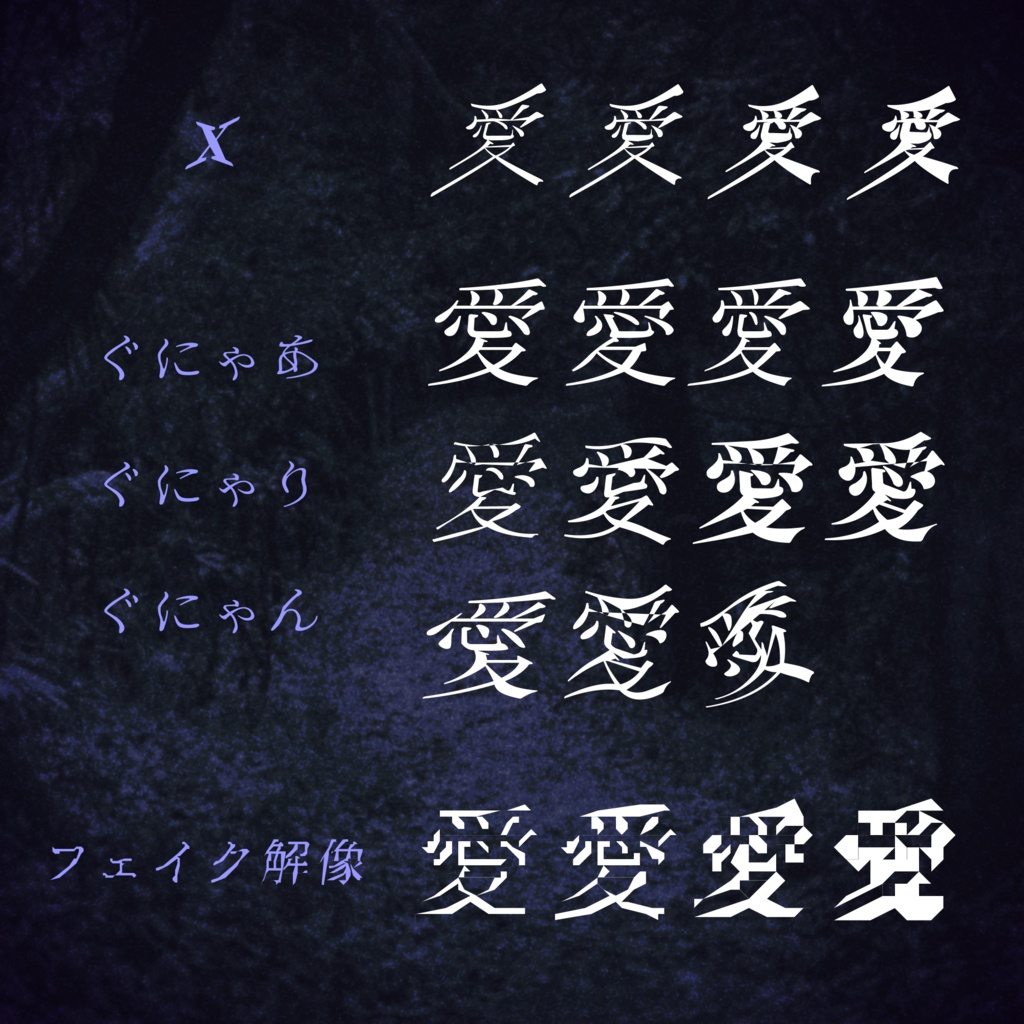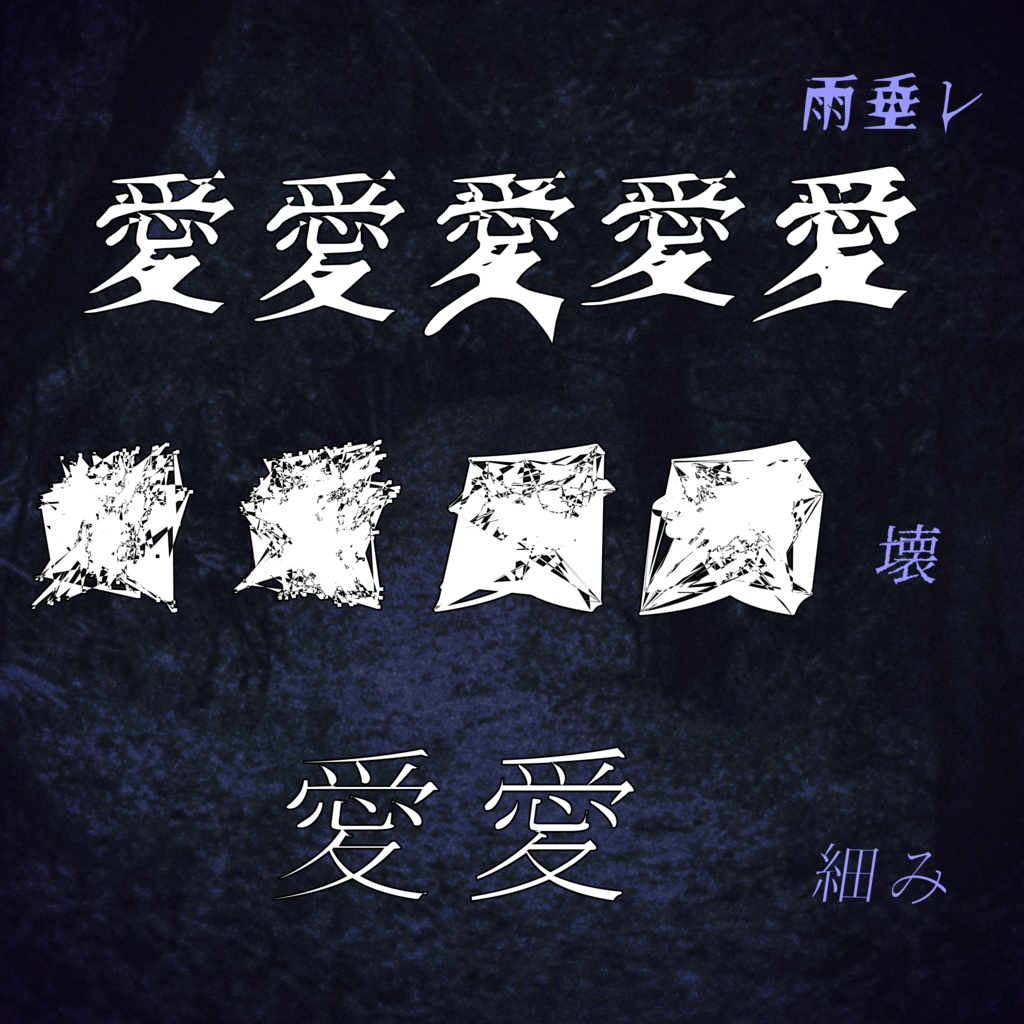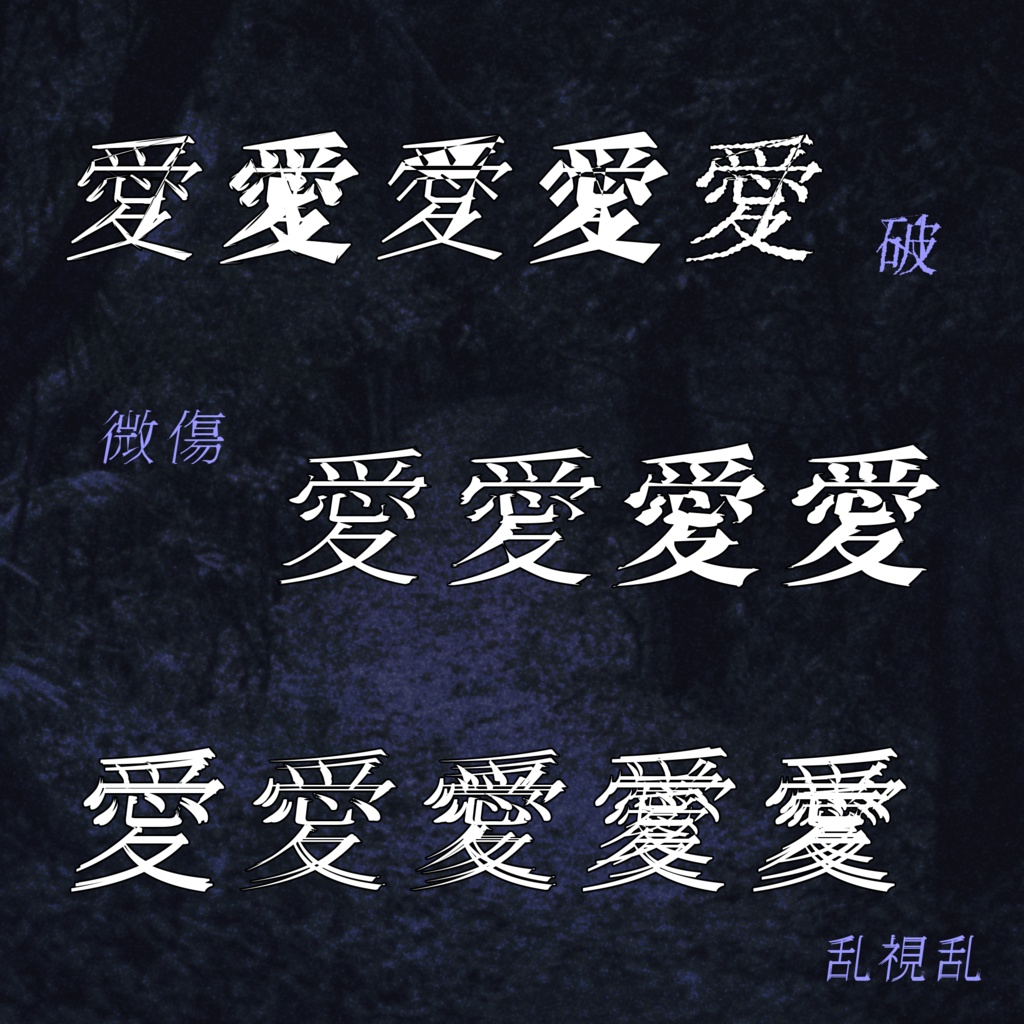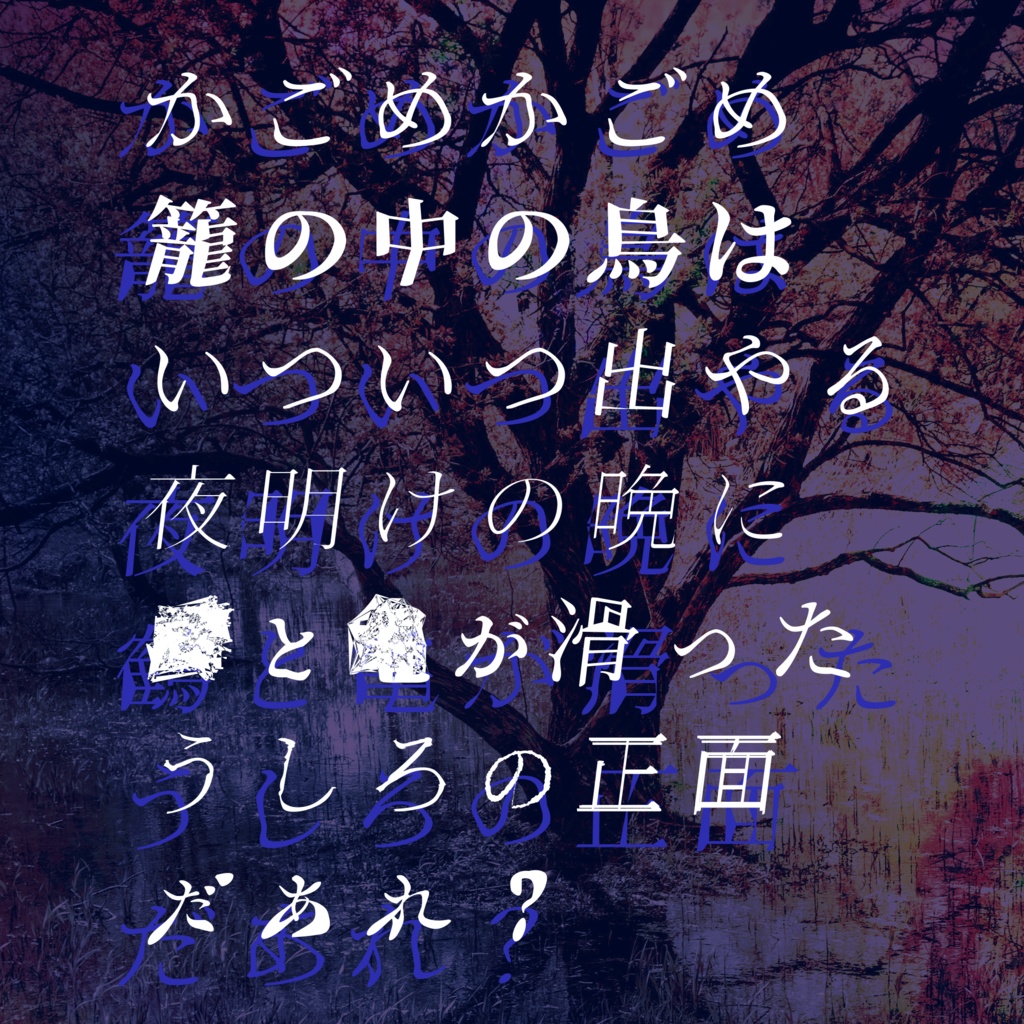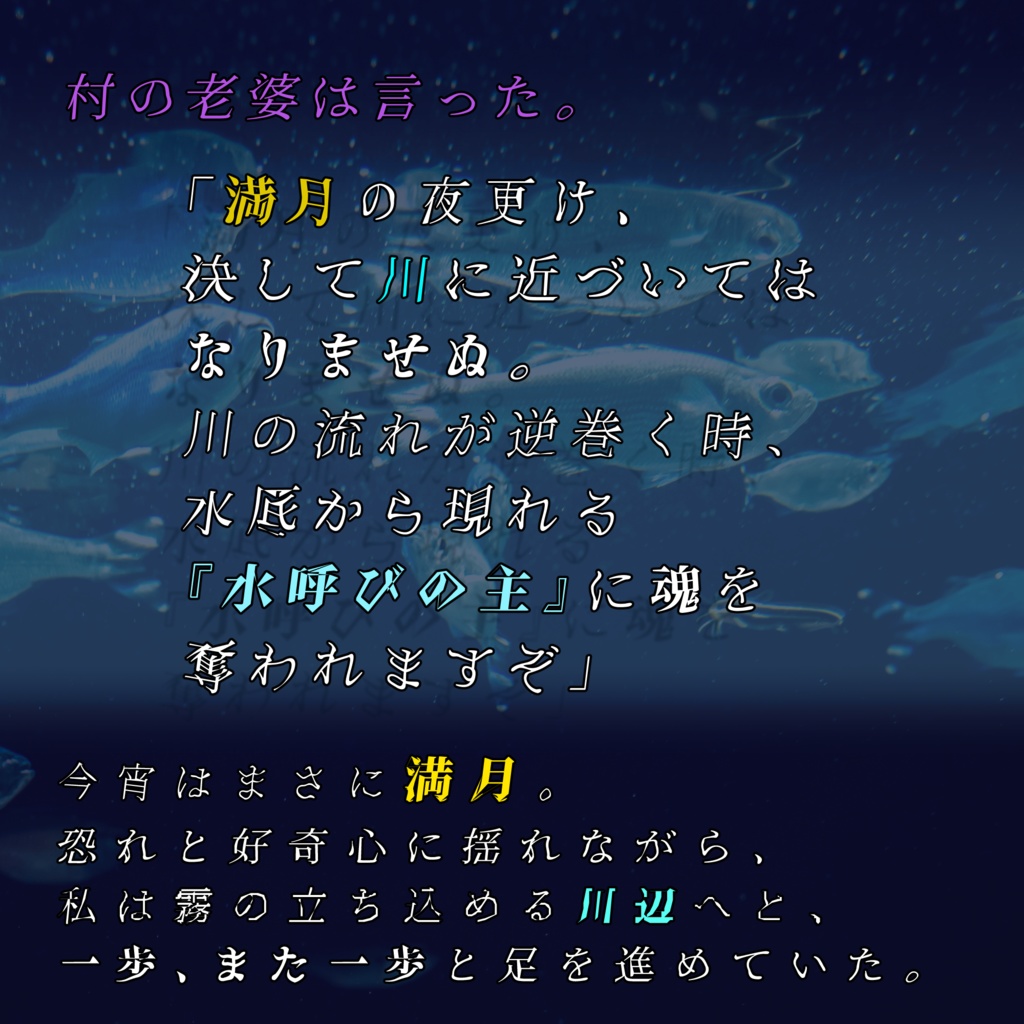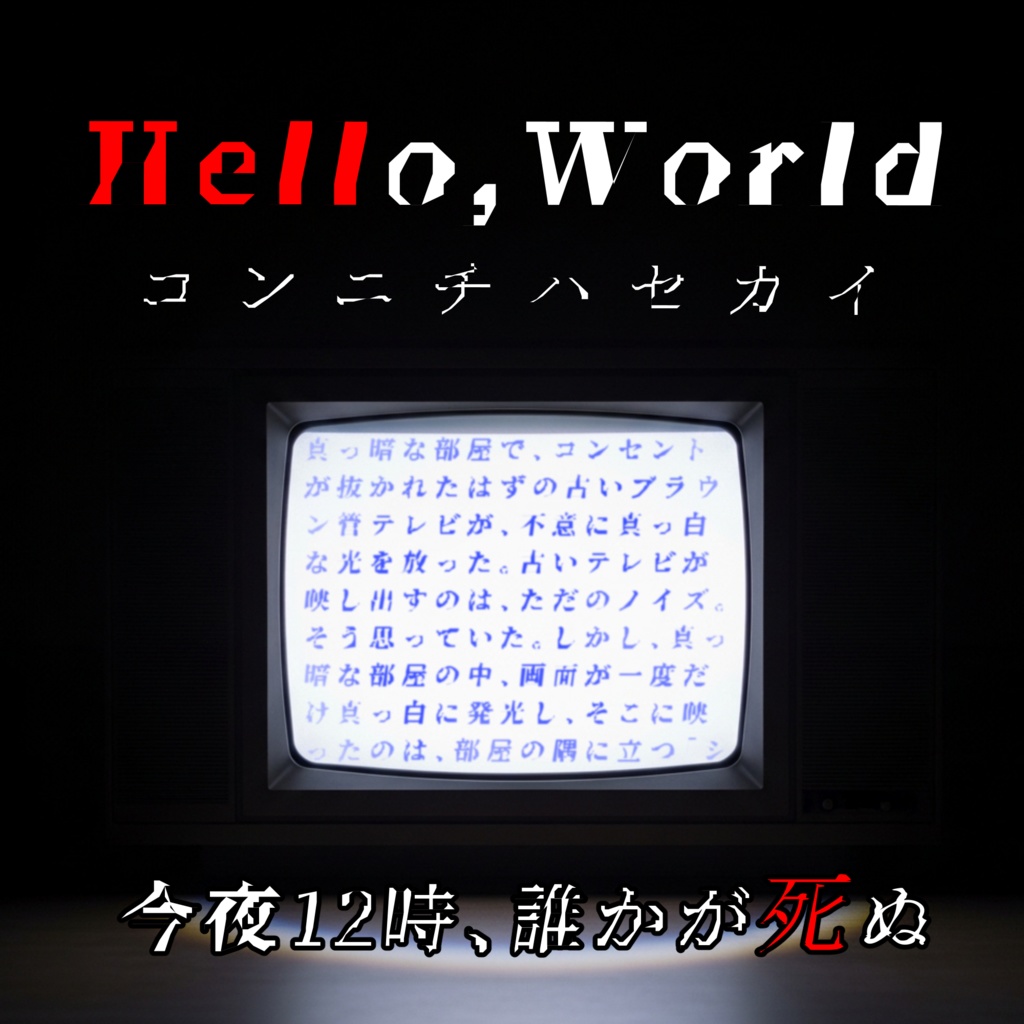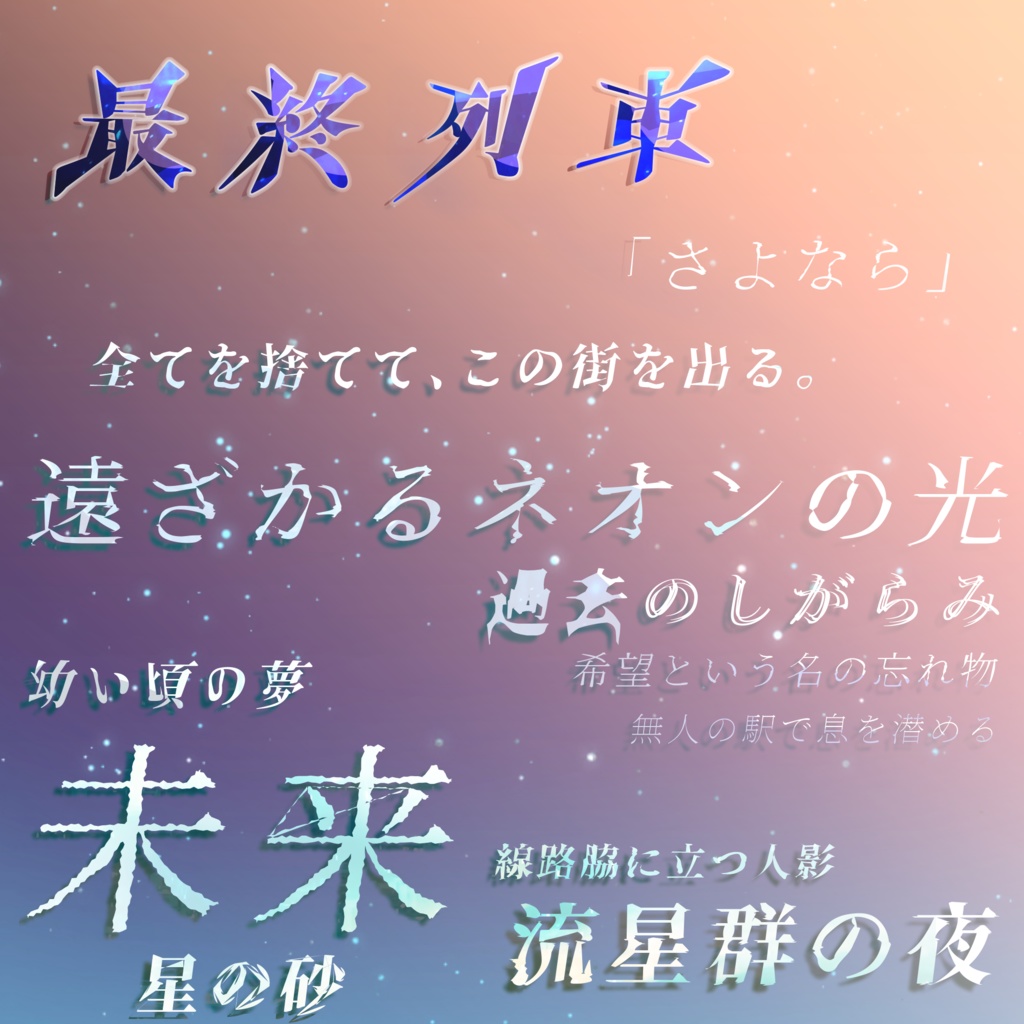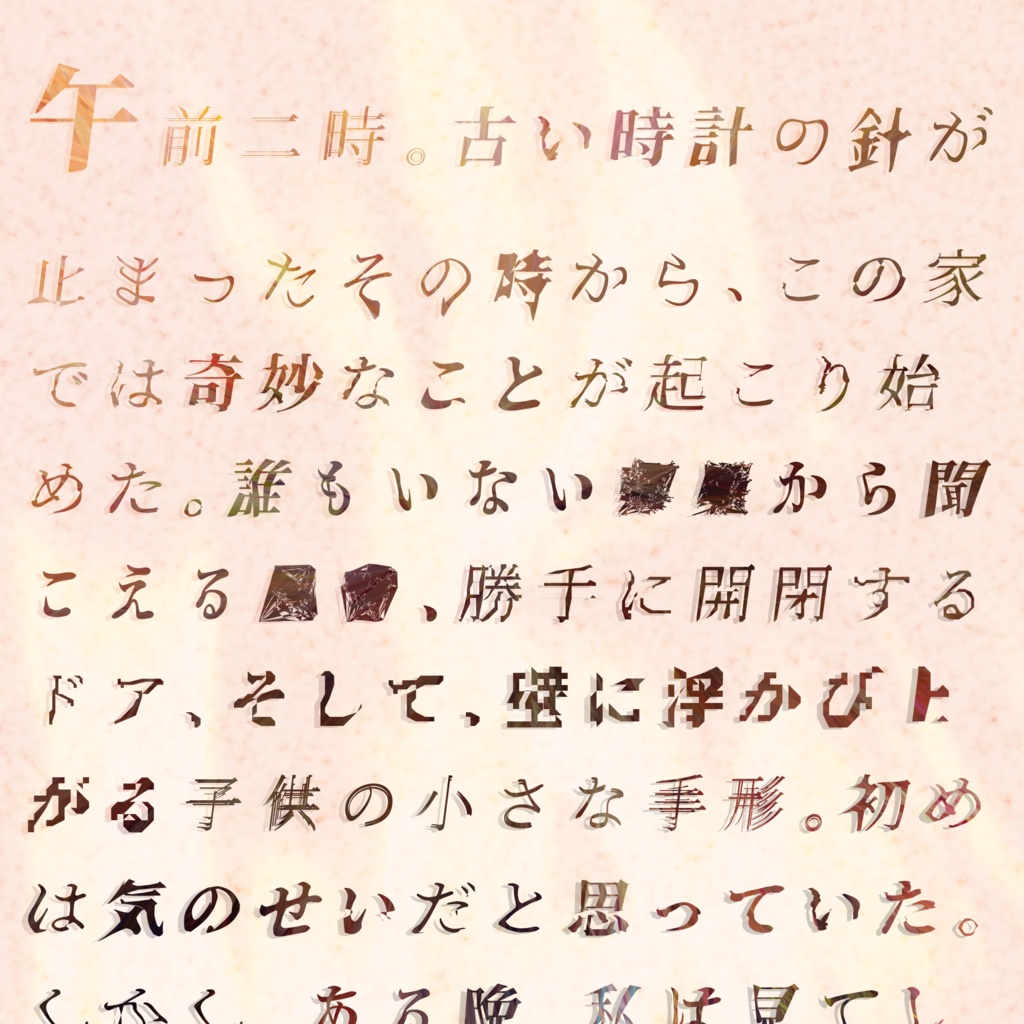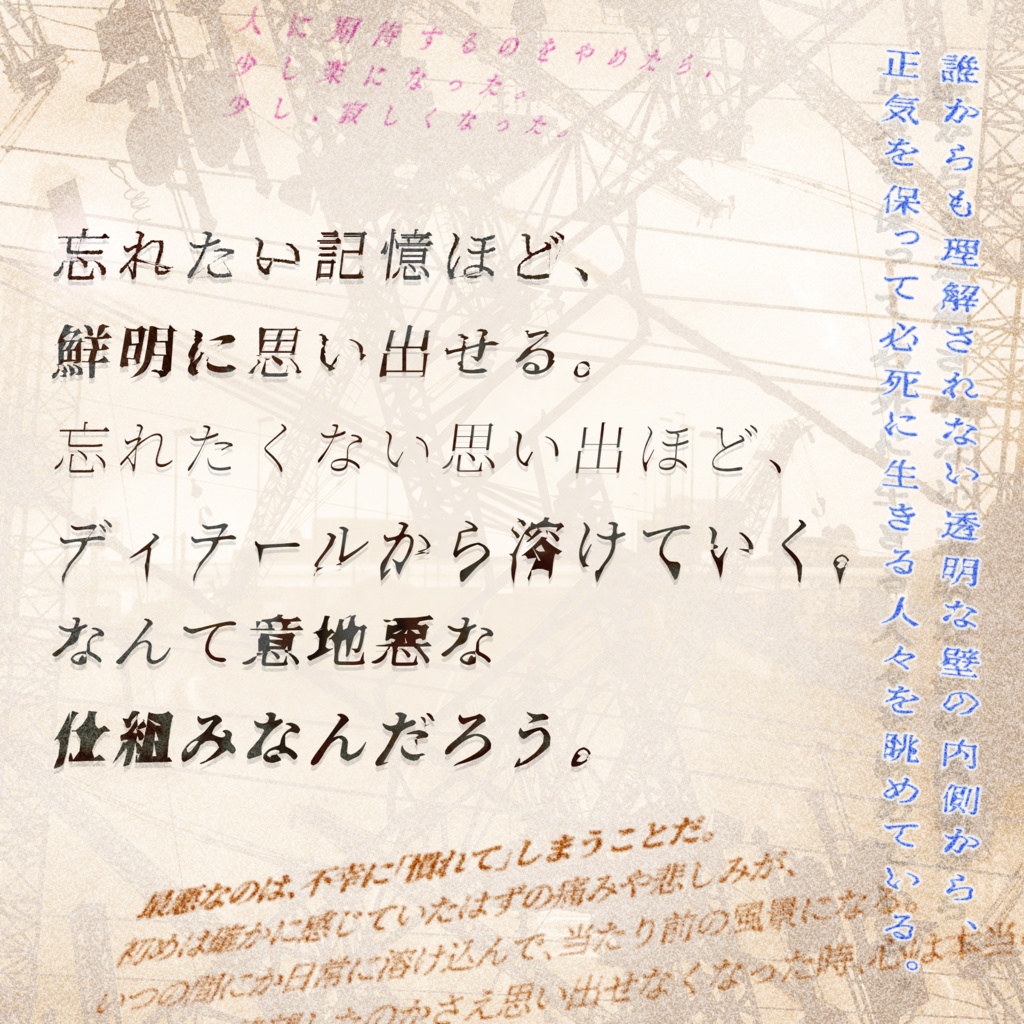
あやしげ書体『流怪譚』【フリーフォント】
『流怪譚』(Ryukaitan) 怪しげ・不穏な雰囲気、あるいは実験的な効果のフォント集です。 ホラーゲーム、動画、TRPGのシナリオなど、作品に一癖加えたい時に。
● X レンズ効果をかけたように、全体がX状に変形したフォントです。 ● ぐにゃあ ● ぐにゃり ● ぐにゃん 正気を失った視界のように、ぐにゃりと揺らめくフォントです。 ● フェイク解像 粗い視界や低い解像度を表現できるフォントです。 ● 雨垂レ 文字が液状化し、下方に垂れたような加工のフォントです。インクの滲みやドロリとした心情のような表現に。 ● 壊 プログラムのバグにより生まれた、文字がグシャッと塗り潰されたような表現に使えるフォントです。 ● 細み ベースフォント『02Ryusenkei-ExtraLight』をさらに細字化し、ニュアンスを付加したベーシックなフォントです。 ● 破 プログラムのバグにより生まれた、独特なアクセントとノイズが走るフォントです。文字によっては字形の破綻が大きいため、特にクセが強いフォントです。 ● 微傷 わずかな横揺れが、見る者に不安や違和感を抱かせるフォントです。 ● 乱視乱 乱れた視界のように、幾重にも字形が重なって表示されるフォントです。